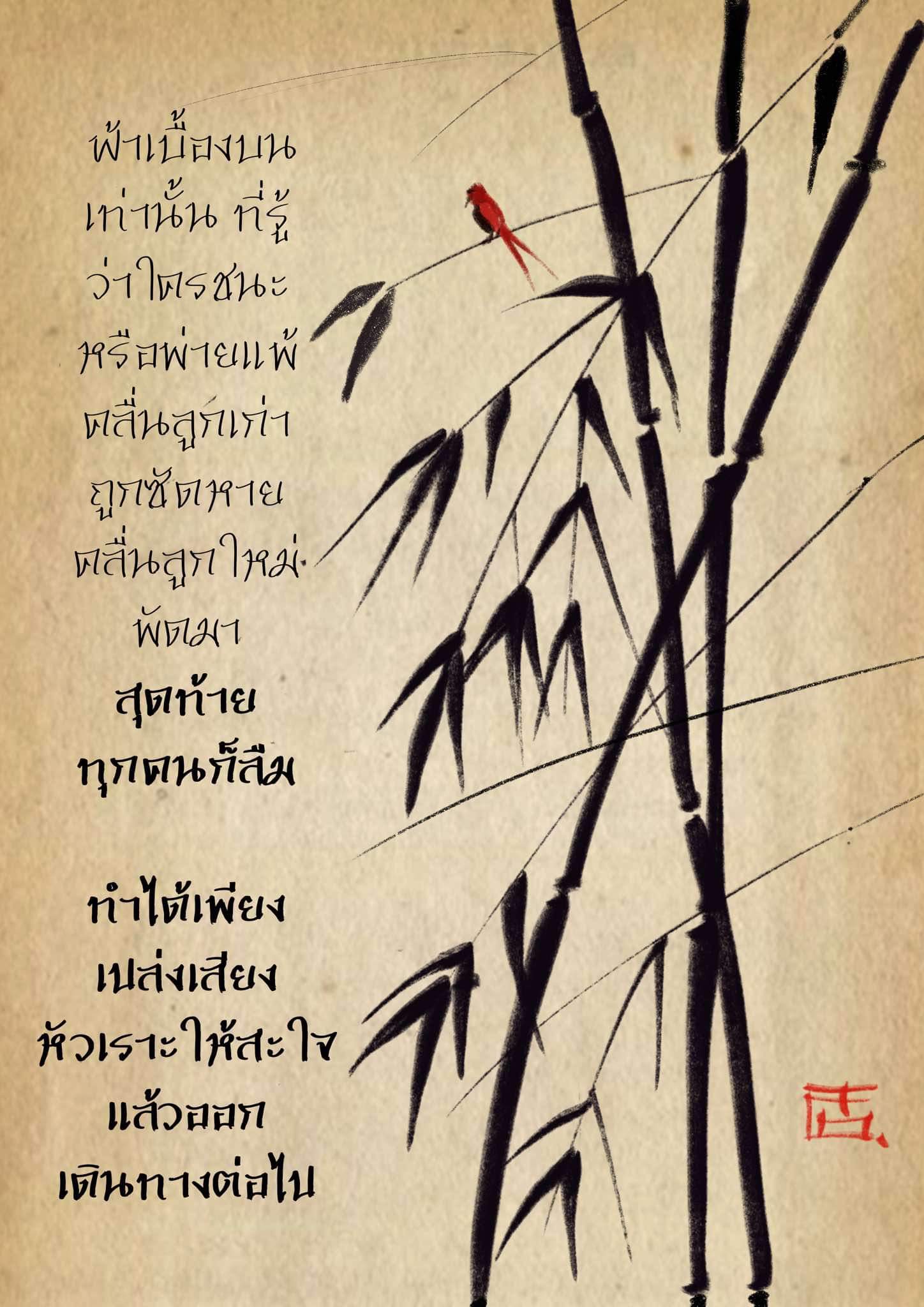
บูรพาไม่แพ้
ชื่อฟอนต์  บูรพาไม่แพ้
เป็นฟอนต์ที่ได้แรงบันดาลใจมาจากภาษาจีนอีกตัวนึงครับ ฟอนต์ตัวนี้ทำมาสองน้ำหนักคือ ตัวปกติ และตัวบาง
ออกแบบโดย
ระจัน โรงเรียนสอนศิลปะทอศิลป์